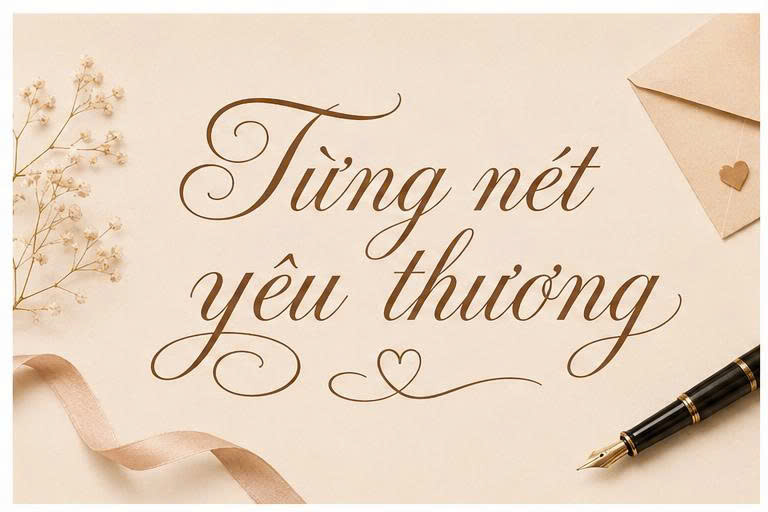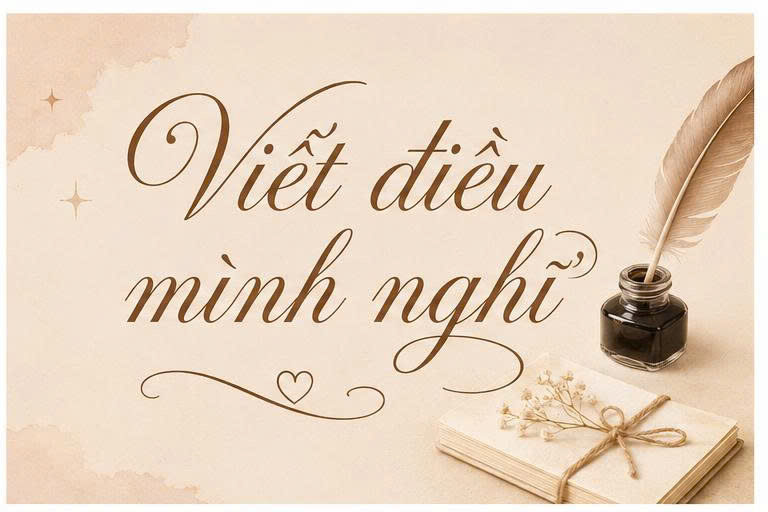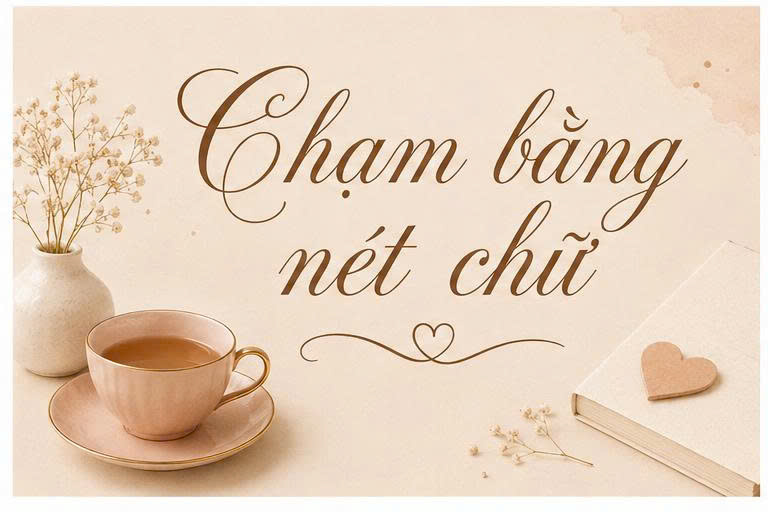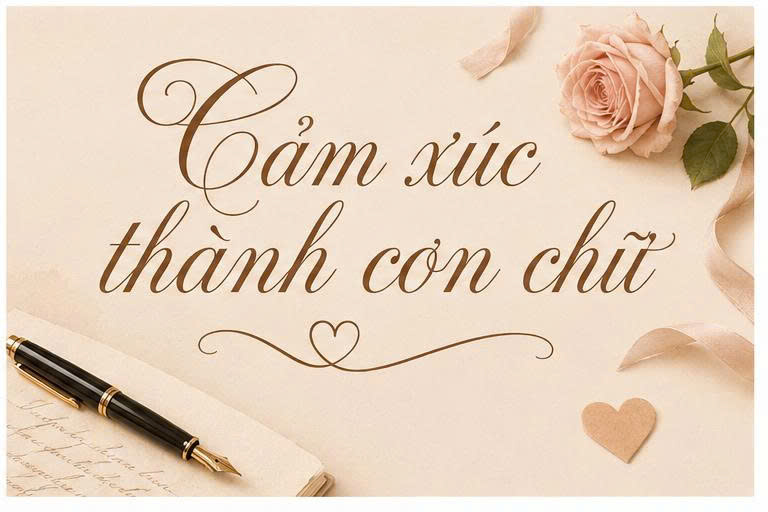
Font Việt hóa SVN Darleston là bộ phông chữ thuộc dòng Calligraphy Script mang phong cách thanh lịch, lãng mạn với những đường nét uốn lượn bay bổng và cực kỳ tinh tế. Với đặc trưng là các nét nối dài thướt tha và độ tương phản nét thanh đậm rõ rệt, SVN Darleston đã trở thành lựa chọn hàng đầu cho các thiết kế thiệp cưới, nhãn hàng mỹ phẩm cao cấp và bao bì quà tặng. Doozypack.vn cung cấp link tải font SVN Darleston chuẩn, giúp bạn sở hữu bộ font SVN Darleston Việt hóa không lỗi dấu thanh để nâng tầm thẩm mỹ cho mọi ấn phẩm thiết kế.
Đặc điểm thẩm mỹ của font SVN Darleston Việt hóa
Darleston không chỉ là một phông chữ viết tay thông thường; nó là sự kết hợp giữa kỹ thuật đưa bút điêu luyện và ngôn ngữ đồ họa sang trọng đương đại.
Đường nét uốn lượn mềm mại và quý phái
Đặc trưng lớn nhất của font Việt hóa SVN Darleston là hệ thống các ký tự có nét hất (swashes) rất dài và mượt mà. Cấu trúc chữ có độ nghiêng nhẹ nhàng, tạo cảm giác như được viết bởi một nghệ nhân thư pháp chuyên nghiệp. Nhịp điệu của các con chữ khi đứng cạnh nhau tạo nên một dòng văn bản trôi chảy, mang lại diện mạo vô cùng đẳng cấp và nữ tính cho tiêu đề bản thiết kế.
Hệ thống dấu tiếng Việt được tối ưu chỉn chu
Nằm trong bộ sưu tập SVN (Style Việt hóa) danh tiếng, Darleston đã được đội ngũ thiết kế tinh chỉnh lại hoàn toàn hệ thống dấu thanh tiếng Việt. Các dấu sắc, huyền, hỏi, ngã, nặng được đặt ở vị trí cân đối, hài hòa với cấu trúc mảnh mai của thân chữ, đảm bảo văn bản luôn giữ được sự thanh thoát, không bị rối mắt hay chồng chéo nét ngay cả khi in trên các bề mặt nhỏ như tem nhãn nước hoa.
- Tạo dấu ấn Luxury: Darleston giúp bao bì toát lên vẻ quý phái, đặc biệt phù hợp với các thương hiệu thời trang, spa làm đẹp và quà tặng doanh nhân cao cấp.
- Giải quyết lỗi hiển thị: Việc sử dụng bản Việt hóa chuẩn giúp bạn gõ các slogan như “Gửi trọn tình thân” hay “Sắc đẹp vĩnh cửu” một cách hoàn mỹ, không bị nhảy font ở các ký tự đặc thù.
- Dễ dàng phối hợp: Bạn có thể kết hợp Darleston (làm tiêu đề) với một font không chân (Sans-serif) thanh lịch để tạo sự cân bằng và hiện đại cho bản thiết kế.
Ứng dụng thực tế của font Darleston tại Doozypack.vn
Vẻ đẹp quý phái của Darleston mang lại hiệu quả thị giác đặc biệt trên các ấn phẩm thực tế do Doozypack.vn sản xuất:
- Hộp mỹ phẩm & Nước hoa: Sự kết hợp giữa font Darleston và kỹ thuật ép kim vàng (Gold Stamping) trên nền hộp tối màu tạo nên diện mạo vô cùng sang trọng.
- Thiệp mời & Thank you card: Nét chữ script thướt tha của Darleston là lựa chọn tuyệt vời cho các thư ngỏ đi kèm trong hộp quà, thể hiện sự trân trọng đối với khách hàng.
- Tem nhãn sản phẩm làm đẹp: Dùng cho tên dòng sản phẩm hoặc các slogan ngắn trên nhãn dán, tạo cảm giác thư giãn và sạch sẽ cho thương hiệu.